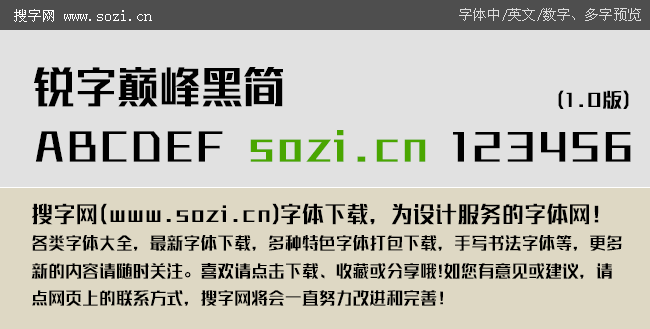
銳字巔峰黑簡(jiǎn)1.0
搜字網(wǎng)提供一款非常藝術(shù)的黑體銳字巔峰黑簡(jiǎn)1.0下載,銳字巔峰黑簡(jiǎn)是一款字形方正的銳字工房字體,該字體極具藝術(shù)感,簡(jiǎn)潔大方,適用于包裝印刷、廣告設(shè)計(jì)、平面設(shè)計(jì)、書(shū)籍報(bào)紙等領(lǐng)域。